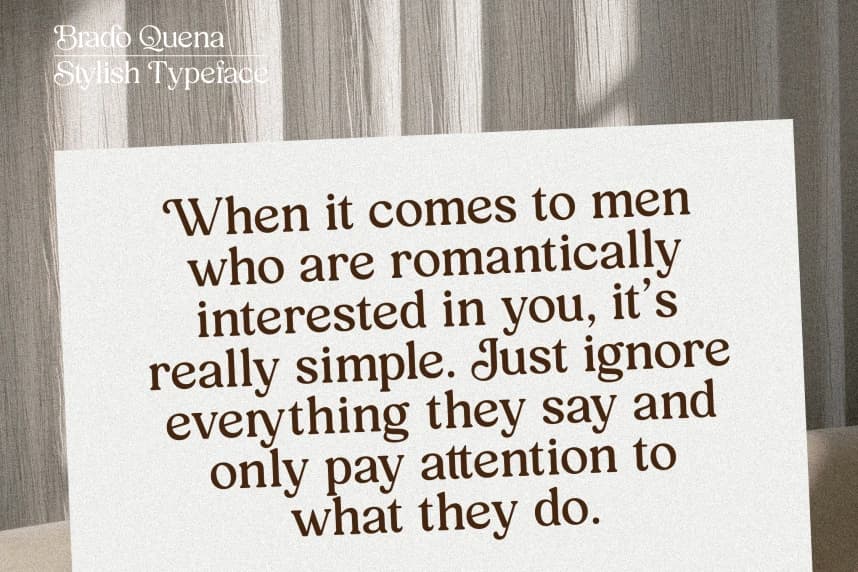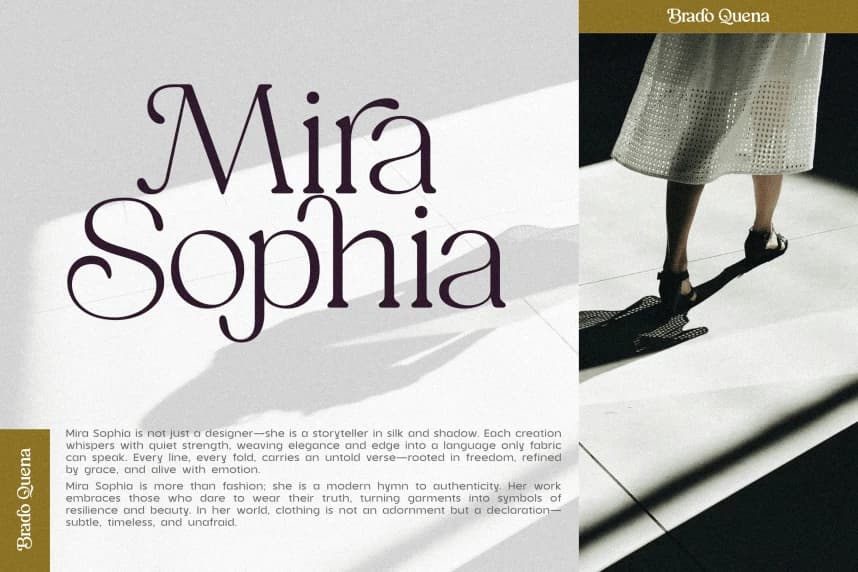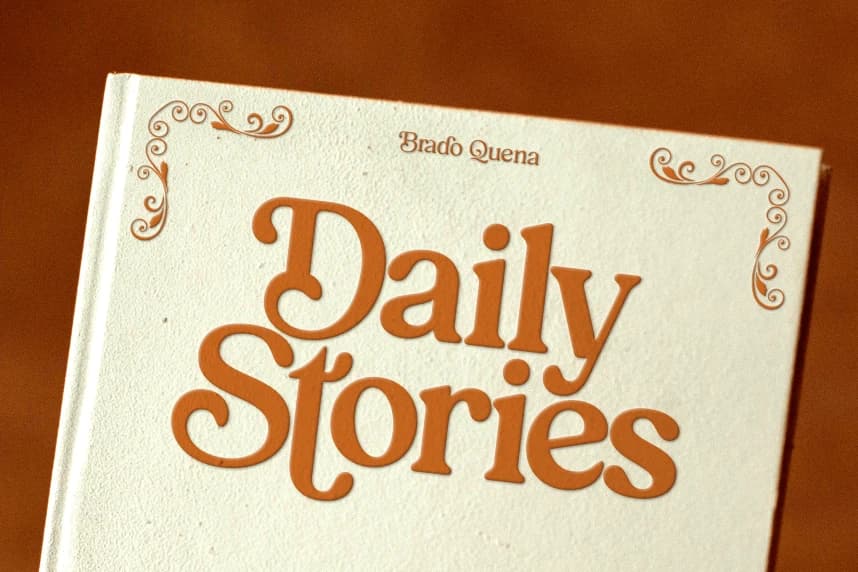
Brado Quena Serif Font
Brado Quena Serif Font, klasik zarafeti çağdaş incelikle birleştiren bir gösteri yazı tipidir. Zamansız güzelliği ve zarif, sofistike bir karakteri ifade etmek için tasarlandı.
Brado Quena Serif Font, klasik zarafeti çağdaş incelikle harmanlayan bir gösterim yazı tipidir. Zamanın ötesinde bir güzellik ve zarif, sofistike bir karakter ifade etmek için tasarlanmıştır.